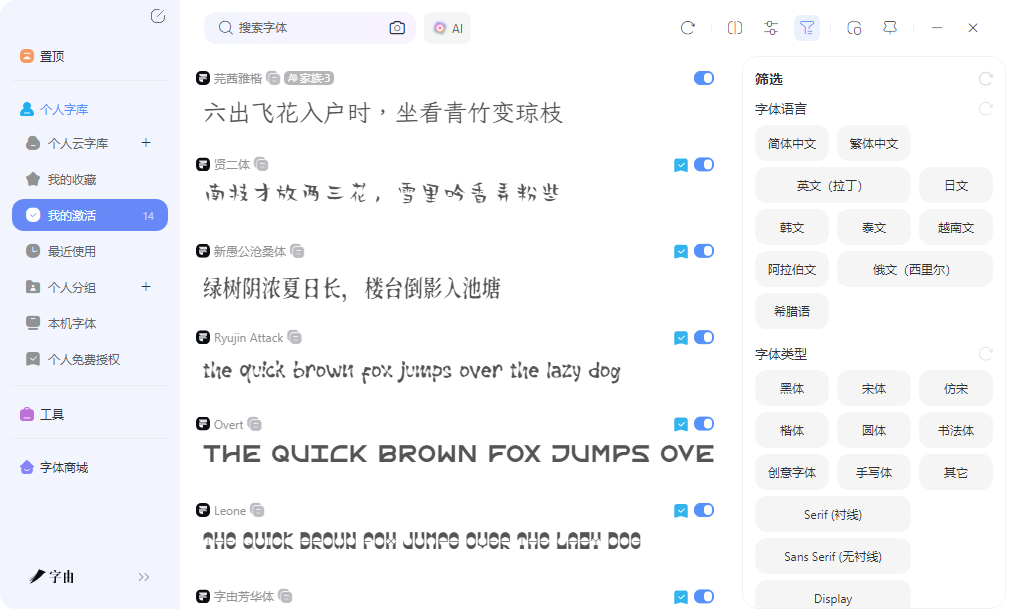
在线字体转换工具推荐,输入文字秒变特效
想要把普通文字变成花体、粗体或手写体,或者在网页上使用自定义字体需要转换文件格式,这些都属于在线字体转换的范畴。这类工具大致分为两类:一类是改变文字外观,另一类是转换字体文件格式(如TTF转WOFF)。本文测试了5款在线字体转换工具,操作难度和输出类型不同,按需选用即可。
字由是国内设计师常用的字体管理平台。它针对文字转换提供了两种方法:一种是通过AI字体功能快速生成带特效的艺术字图片,另一种是通过字体库激活现成字体并在设计软件中反复使用。两条路径都不需要用户下载安装字体文件。
- AI字体功能:打开字由客户端,进入AI字体模块。左侧按风格分类展示模板,包括国潮风、霓虹灯、金属质感、手写书法、电商促销等,共计400多套。每个模板的字体、特效、排版和背景参数已预设完成。用户输入自己的文案,选择一个模板,点击生成按钮,系统输出透明背景的PNG图片。每次生成消耗3个算力点,每日登录赠送6个点,日常使用无需付费。生成的图片可直接用于海报、封面或Banner。
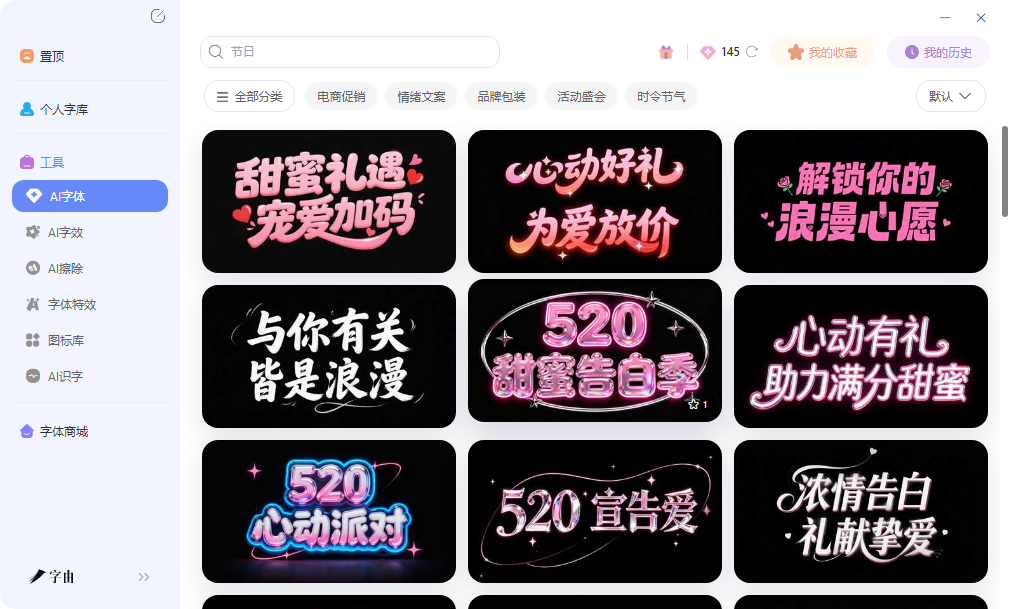
- 字体库激活功能:字由收录了超过10500款字体,其中免费商用字体超过3500款。用户可以通过筛选栏选择字体类型(如手写体、书法体)或语言(简体中文、英文等),预览区输入文字可实时查看效果。找到合适的字体后点击激活按钮,该字体自动出现在PS、AI、Word的字体列表中。用户打开软件输入文字即可使用,不需要下载字体文件,也不需要重启软件。激活的字体通过账号云同步,换设备登录后可在我的激活列表中一键批量激活。取消激活后字体从软件列表消失,不占用系统空间。
字由的这两种方式解决了文字转换中常见的两个问题:一是快速出标题图,二是长期使用可编辑的字体。用户可以根据项目需求选择其中一种,也可以先用AI字体生成预览图给客户确认,确认后再激活同款字体做精细排版。
第四个工具是一个在线字体样式生成器。用户在输入框中输入文字后,下方列出多种Unicode样式选项,包括粗体、斜体、手写体、带圆圈、黑板、德文尖角、全角、无衬线体等。每种样式对应的转换结果以预览形式展示,用户可以点击对应的结果直接复制。该工具生成的是Unicode字符,不是图片,因此可以粘贴到任何支持文本输入的平台(如社交媒体、聊天软件、文档编辑器)。不需要注册,完全免费。
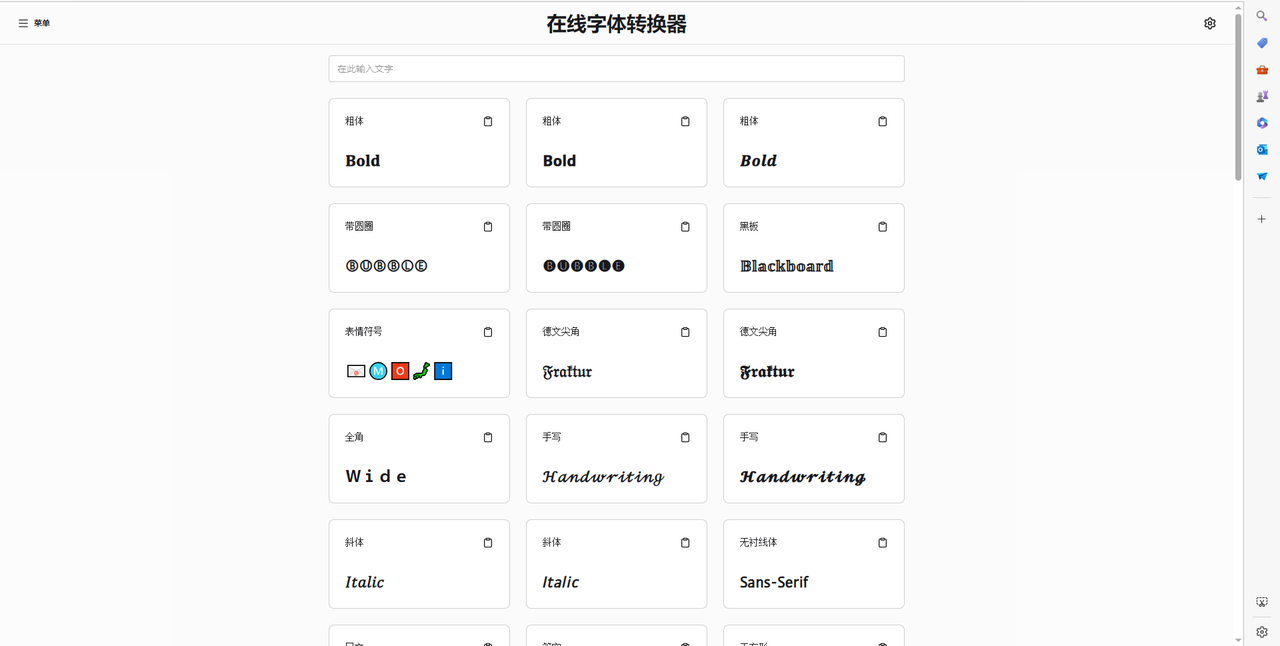
5、字体转换器
第五个网站是一个在线字体转换器页面。用户在输入框中输入文字,下方提供了多种预设字体选项,包括华康娃娃字体、华康海报简体、华文行楷等。每个字体旁边都有查看使用链接,点击可以跳转到字体详情或下载页面。用户可以选择字体大小(默认68像素)、文字颜色(RGB格式)、背景颜色(RGB格式),然后点击提交生成按钮。系统会在下方区域实时显示该文字使用所选字体后的预览效果。
这个工具的核心价值在于快速预览。用户不需要下载安装任何字体文件,也不需要打开任何设计软件,直接在浏览器中输入文字,就能看到华康娃娃字体、华康海报、华文行楷等字体的实际渲染效果。华康娃娃字体圆润可爱,适合儿童主题设计或卡通风格的海报;华康海报简体字重较粗,适合促销标题;华文行楷带有书法笔意,适合中式风格排版。用户可以根据预览效果判断某款字体是否适合自己的项目,再决定是否去下载安装或购买授权。
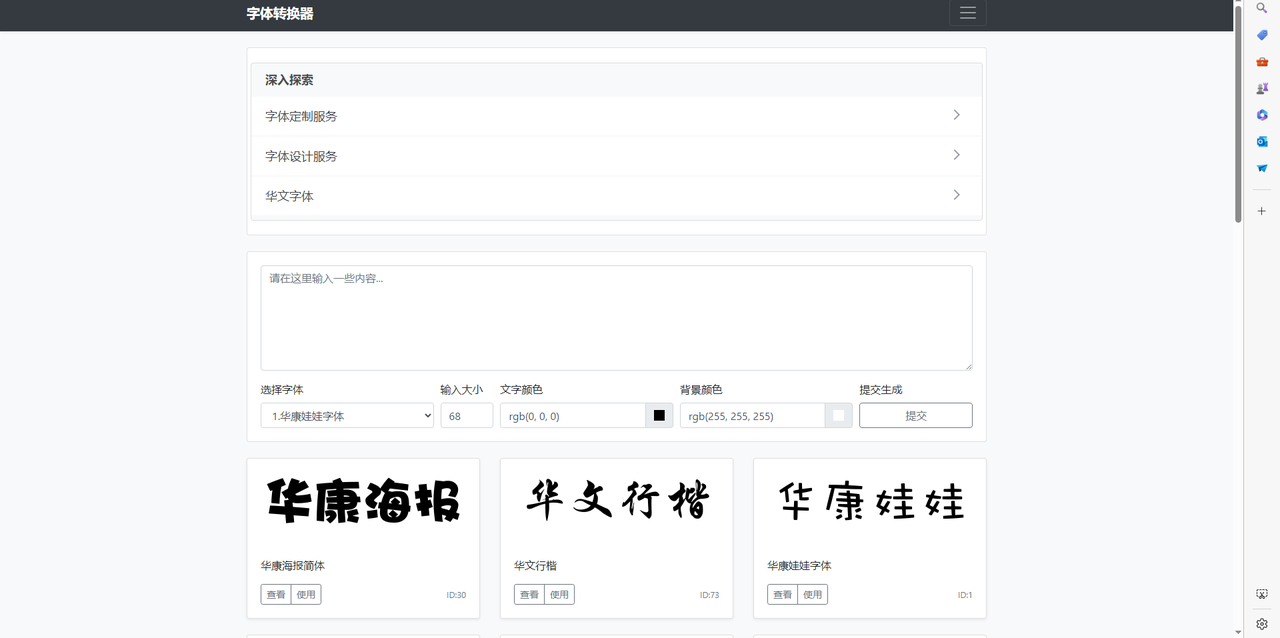
文字外观转换和字体文件格式转换是两种不同的需求。字由的AI字体功能适合需要快速出标题图的场景,400多套模板覆盖国潮、霓虹等风格,每日免费额度够用;字由的字体库激活功能适合需要长期使用可编辑字体的场景,一键激活后在PS和Word中直接打字,多设备同步。其余三款工具的共同点是操作相对传统且功能单一:Text Font Changer在浏览器中改变输入文本的字体样式;NinjaConvert专门用于字体文件格式转换;在线字体样式生成器提供Unicode花式字符复制粘贴。根据自己手头的任务选择最顺手的工具就可以了。